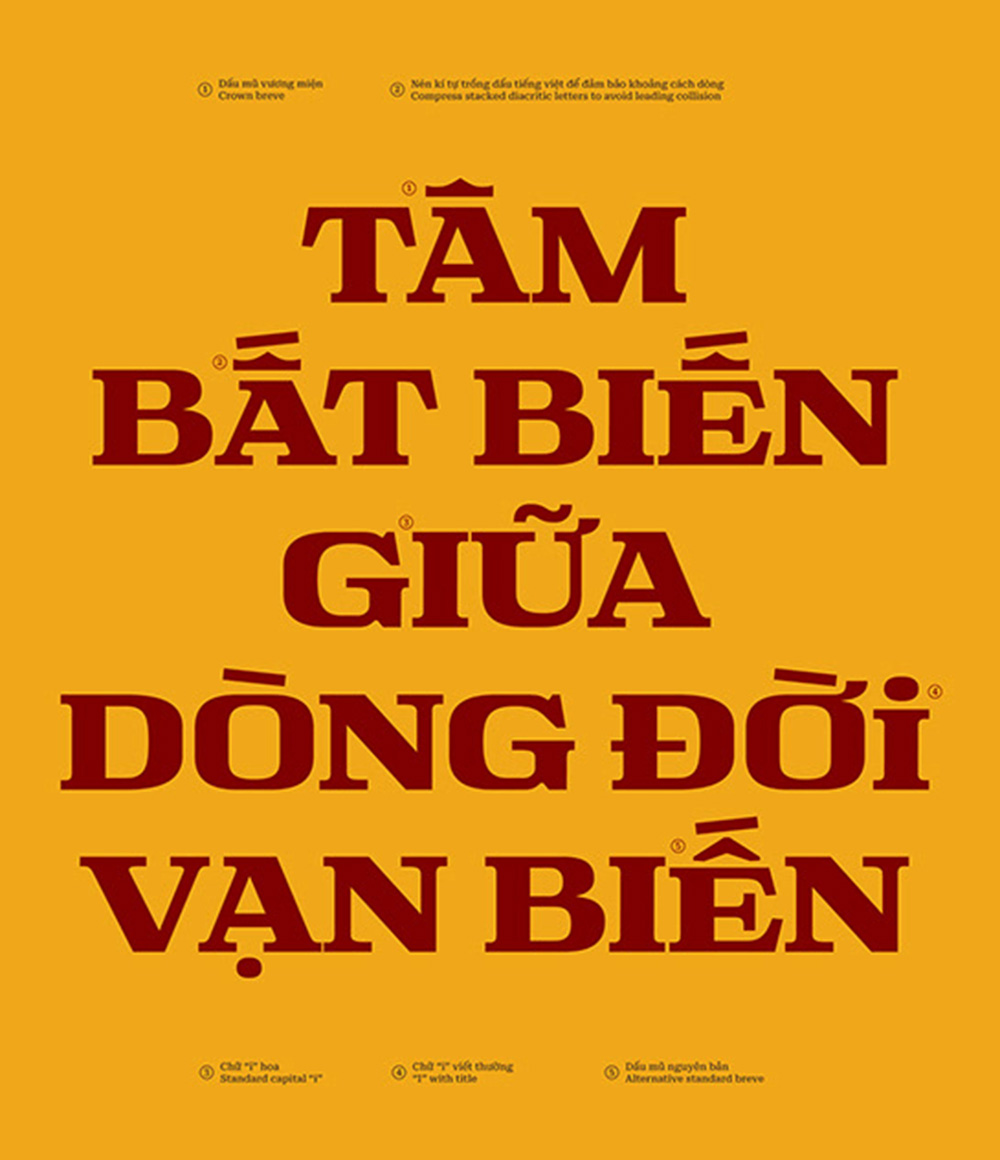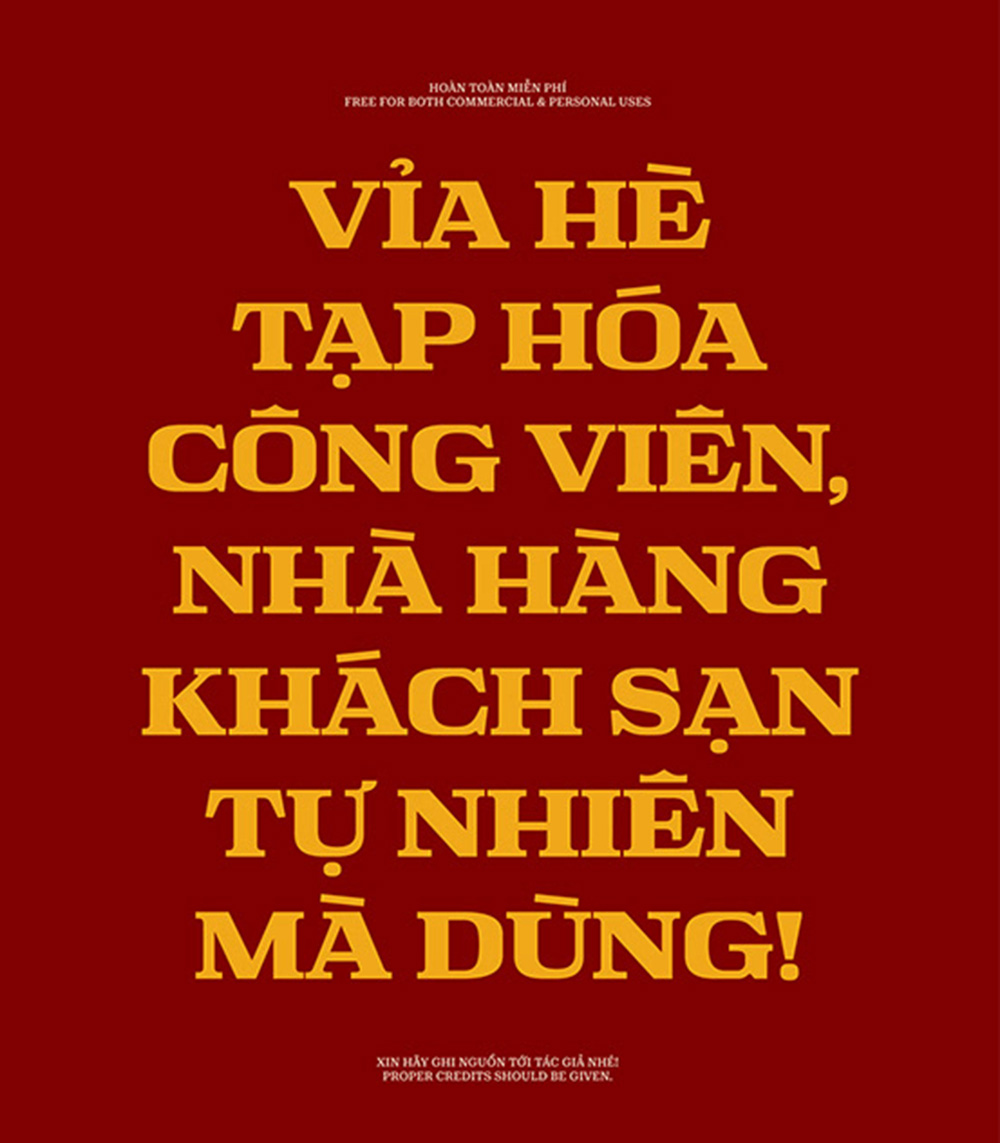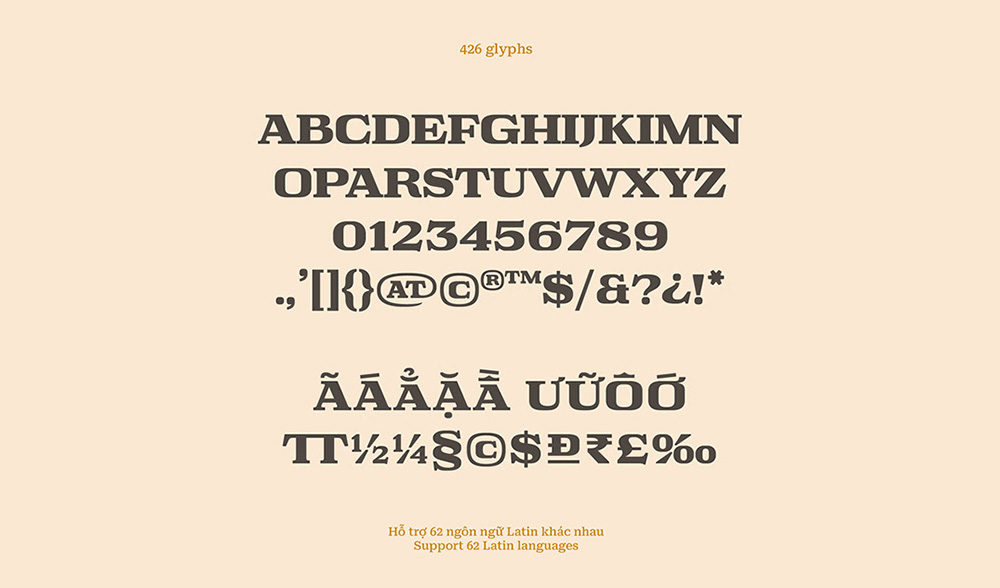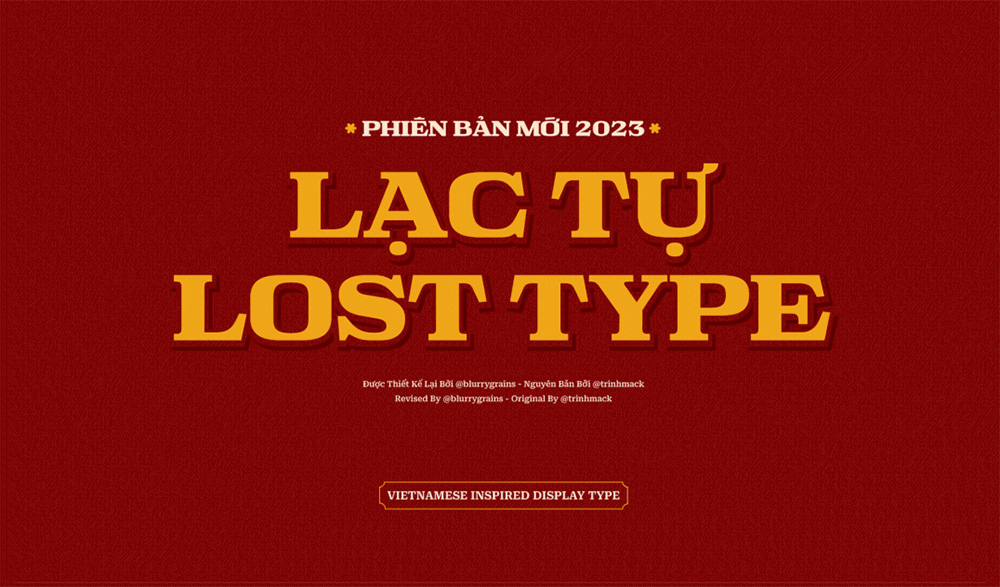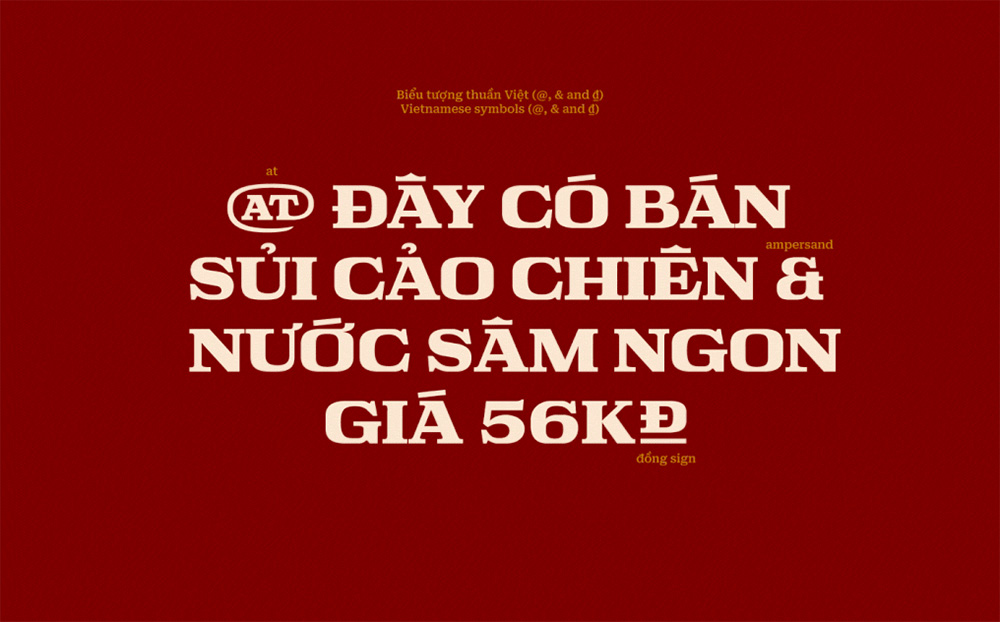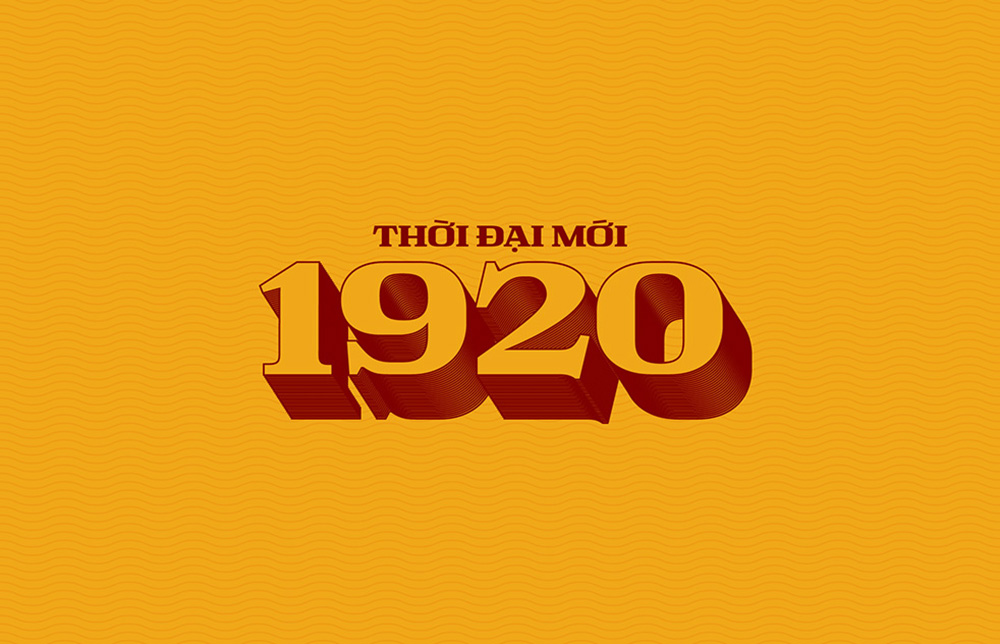
Font Việt Hóa - Lạc Tự ( Phiên Bản Mới 2023) Mang Phong Cách Đô Thị Việt 80s 90s
Lost Type phiên bản mới 2023 mang đến chất lượng hoàn thiện tốt hơn so với phiên bản đầu tiên ra mắt năm 2016. Đây là phông chữ được thiết kế bởi Mack Trinh và Harry Dinh.
Lấy cảm hứng từ mẫu chữ in đậm có chân “quốc dân” được dùng trang trí các bảng hiệu cửa hàng, áp phích và quảng cáo ở mọi ngóc ngách trên đường phố Việt Nam, đặc biệt ở hai thành phố lớn là Hồ Chí Minh và Hà Nội (giữa những năm 1980 và 1990), Lạc Tự 2023 để lại dấu ấn không thể xóa nhòa về cảnh quan đô thị của đất nước hình chữ S, phản ánh tinh thần của một thời đại đã qua.
Lost Type tỏ lòng tôn kính với các phông chữ Slab Serif mang tính biểu tượng như Clarendon. Mặc dù mượn bản chất từ Clarendon, Lost Type có một thiết kế hình hộp và rộng hơn, nâng cao tác động thị giác và khả năng đọc. Tính chất viết hoa của Lost Type còn làm tăng sự hiện diện mạnh mẽ của nó, biến nó thành lựa chọn lý tưởng cho tiêu đề và câu chữ in đậm.